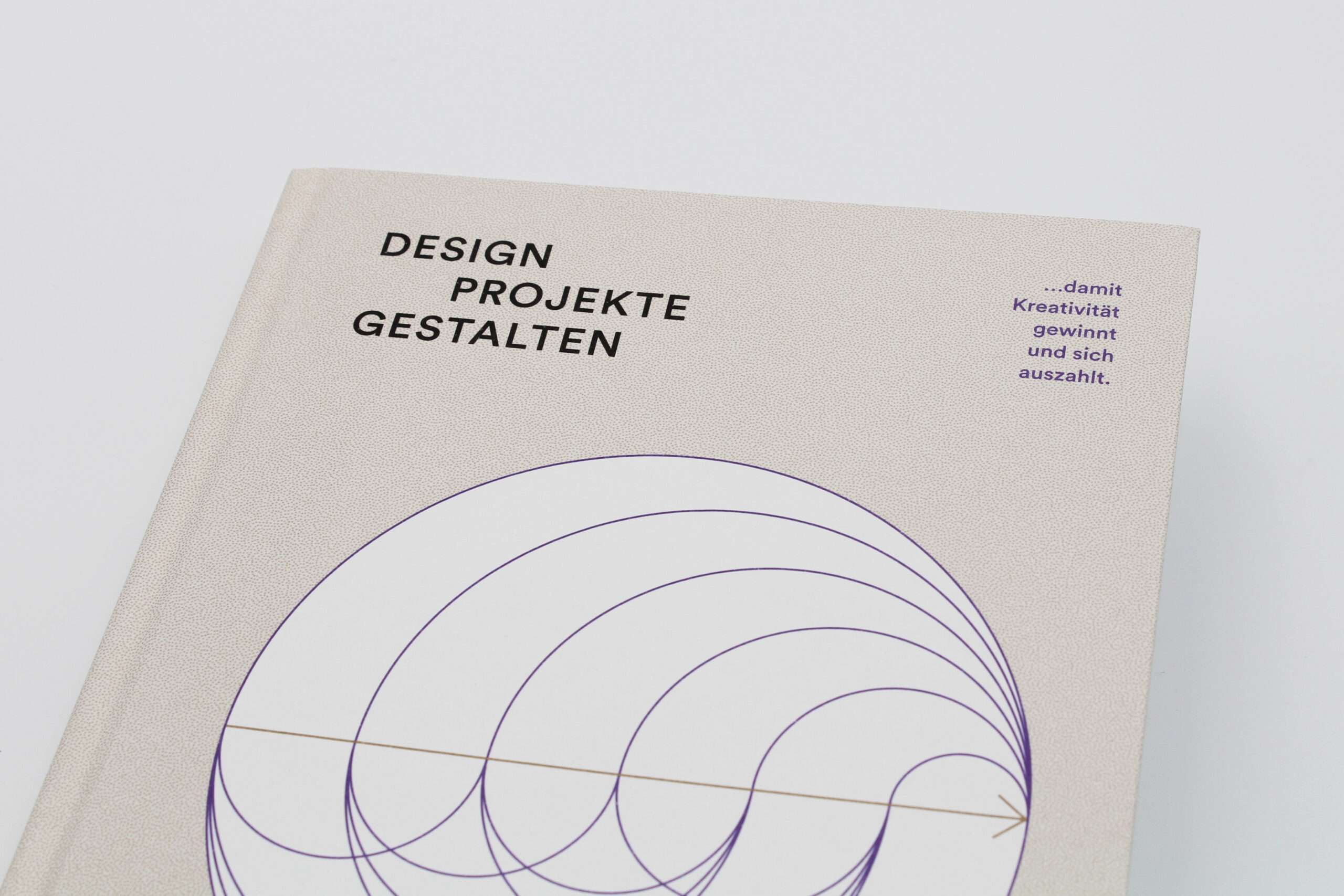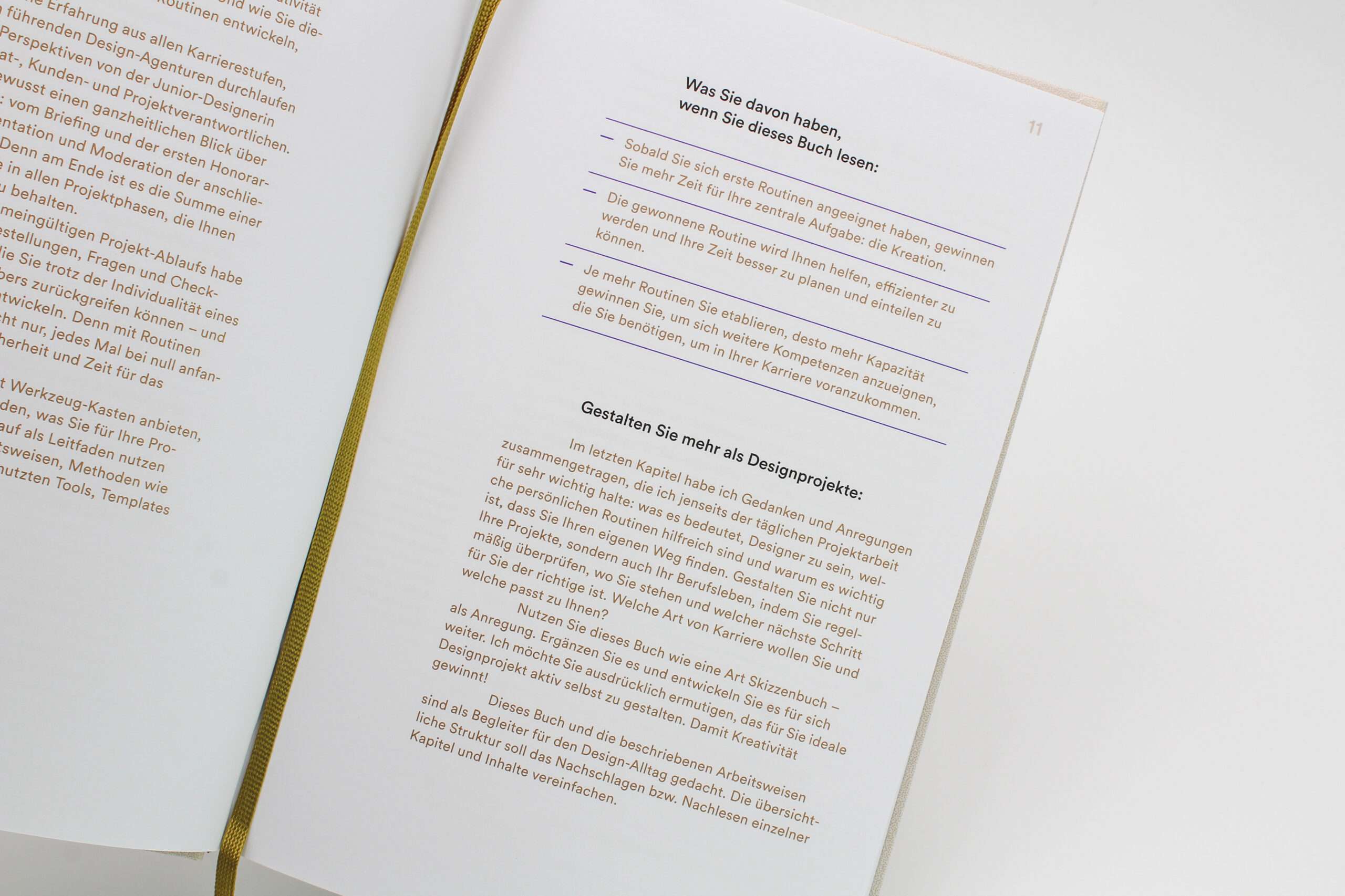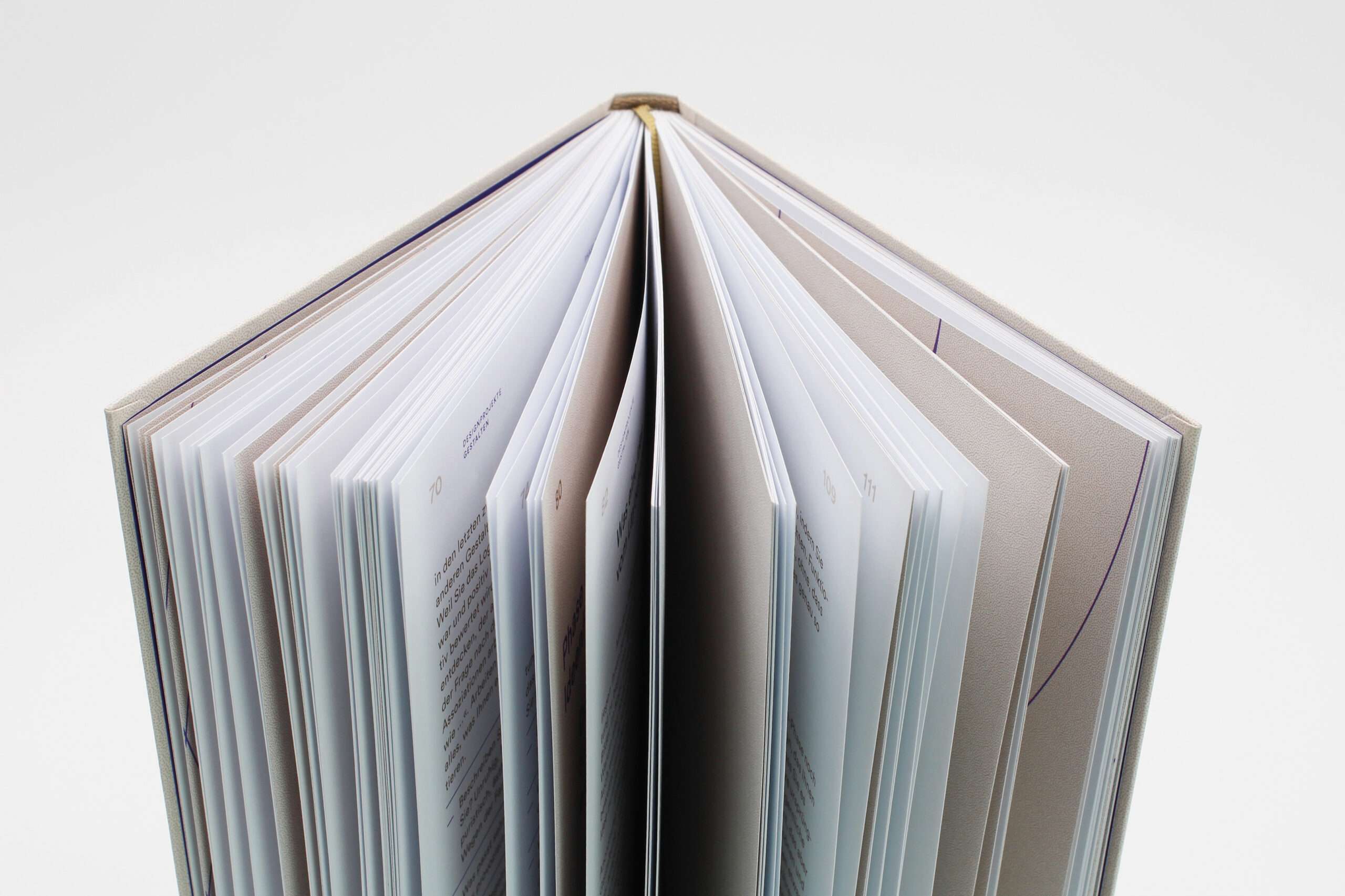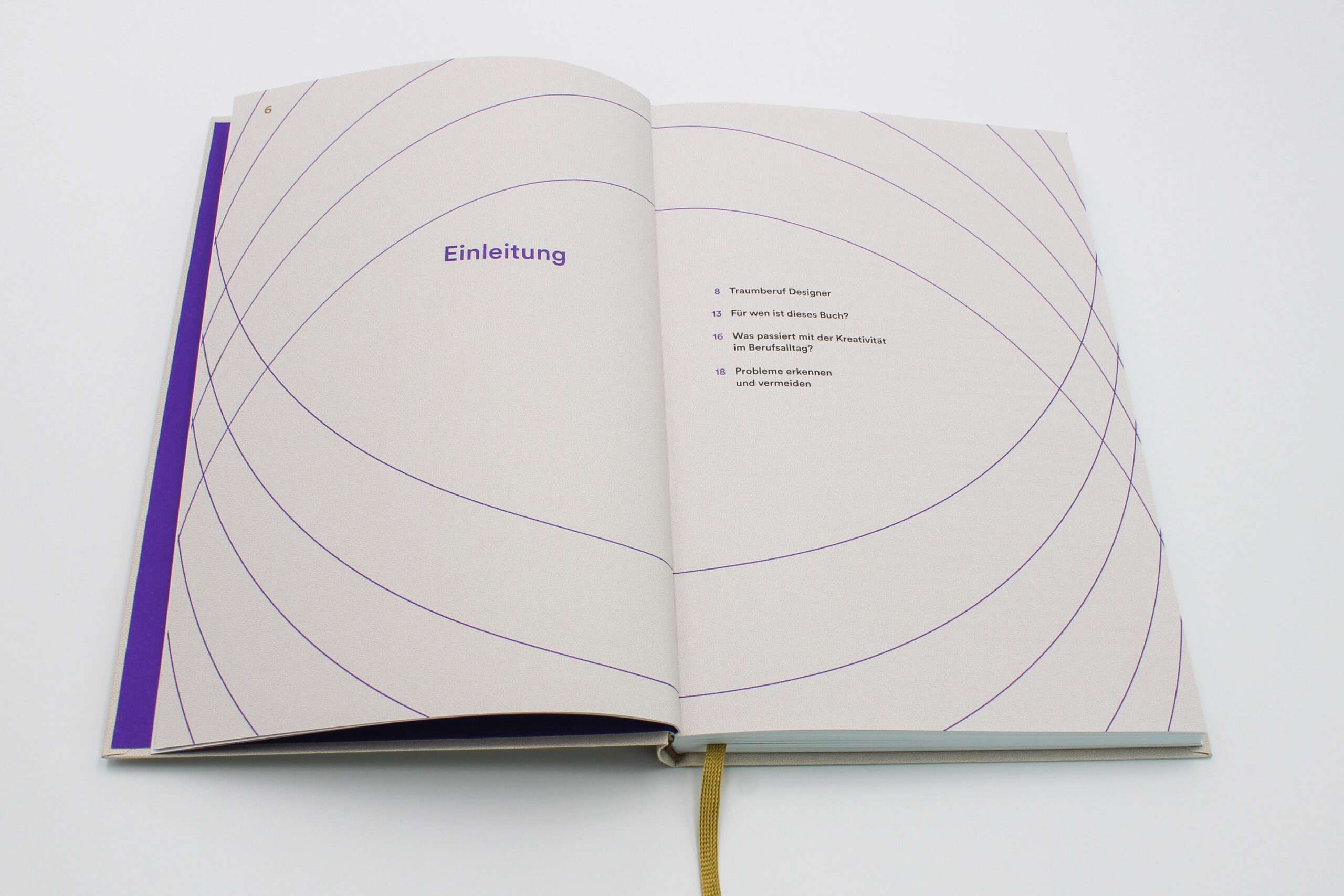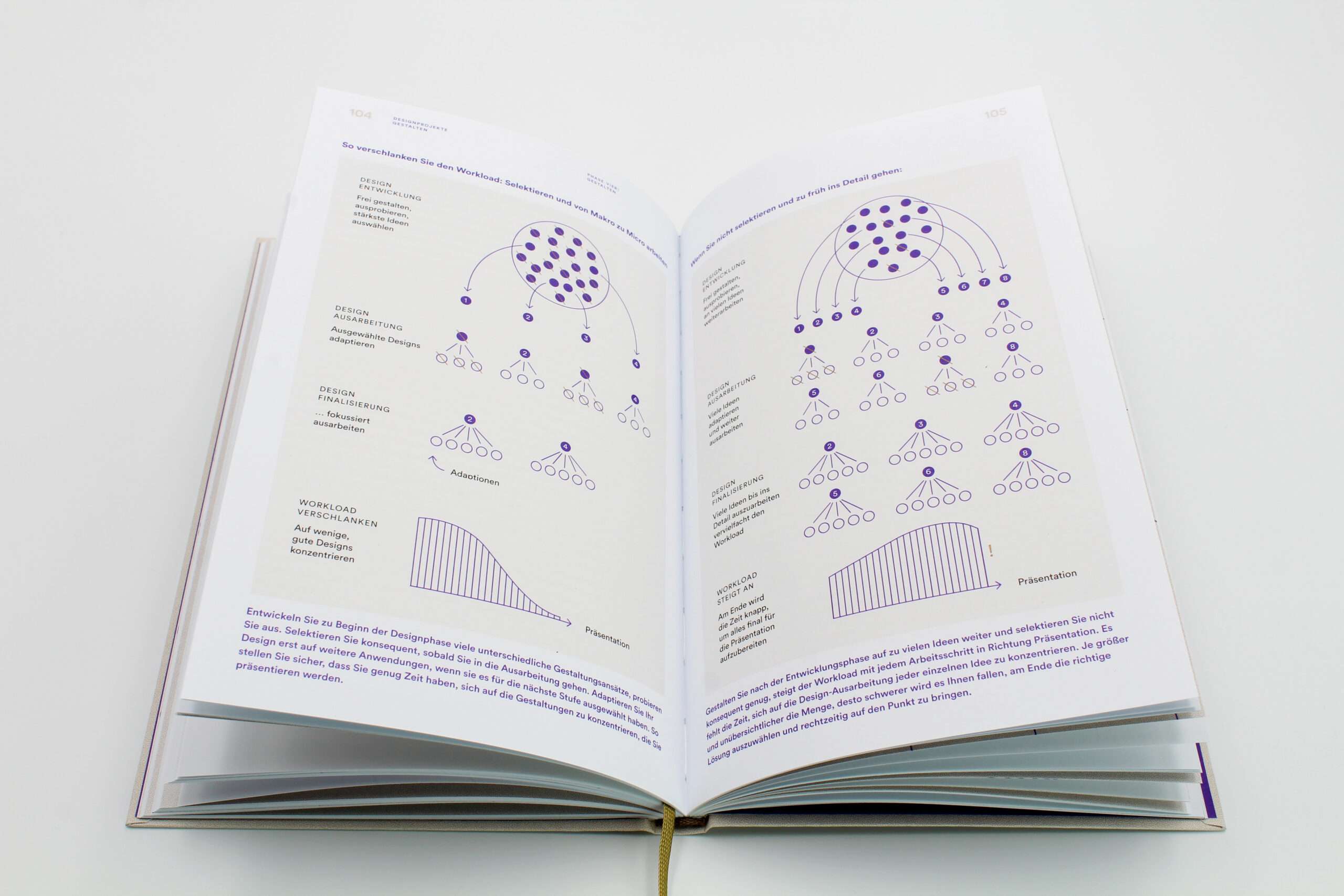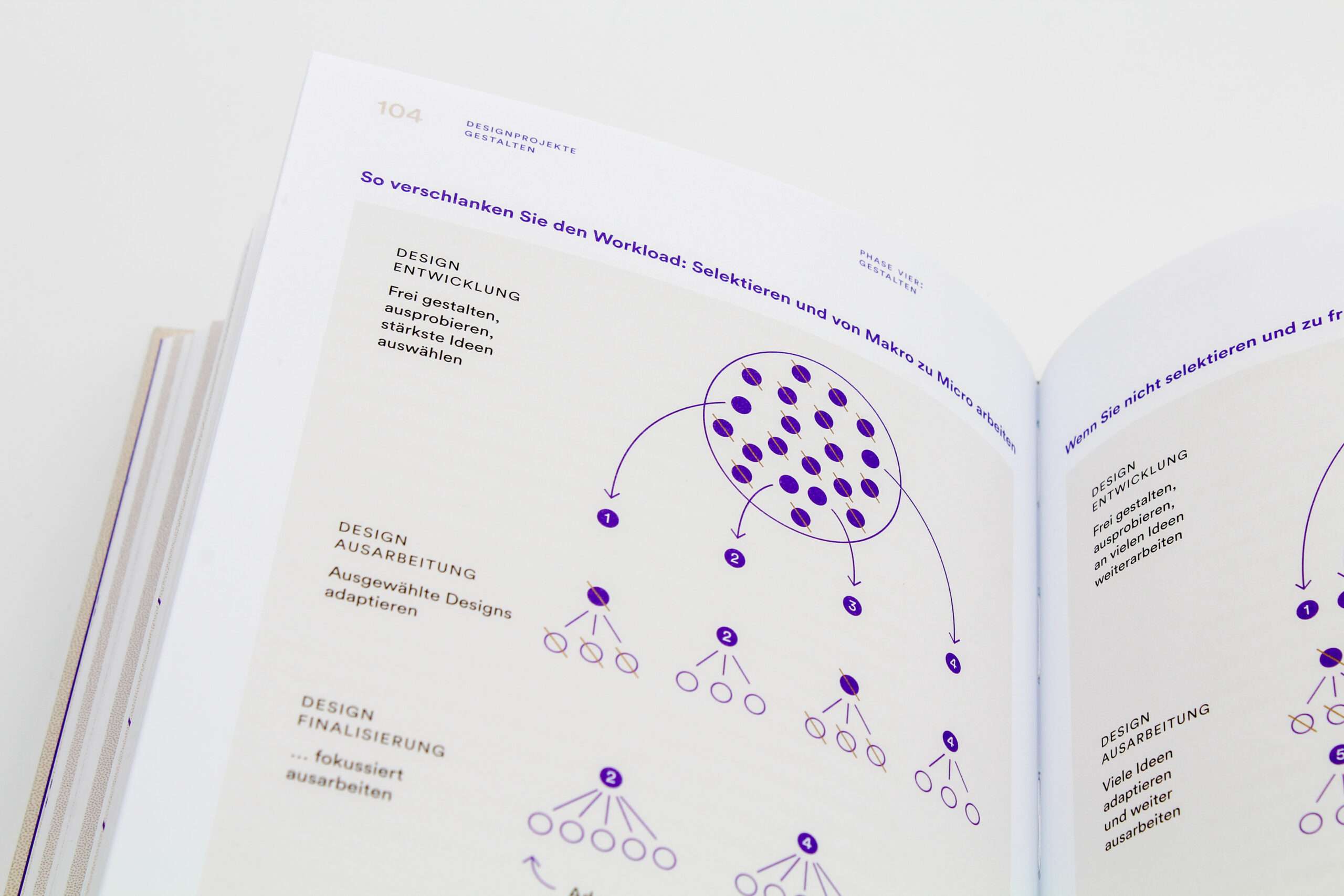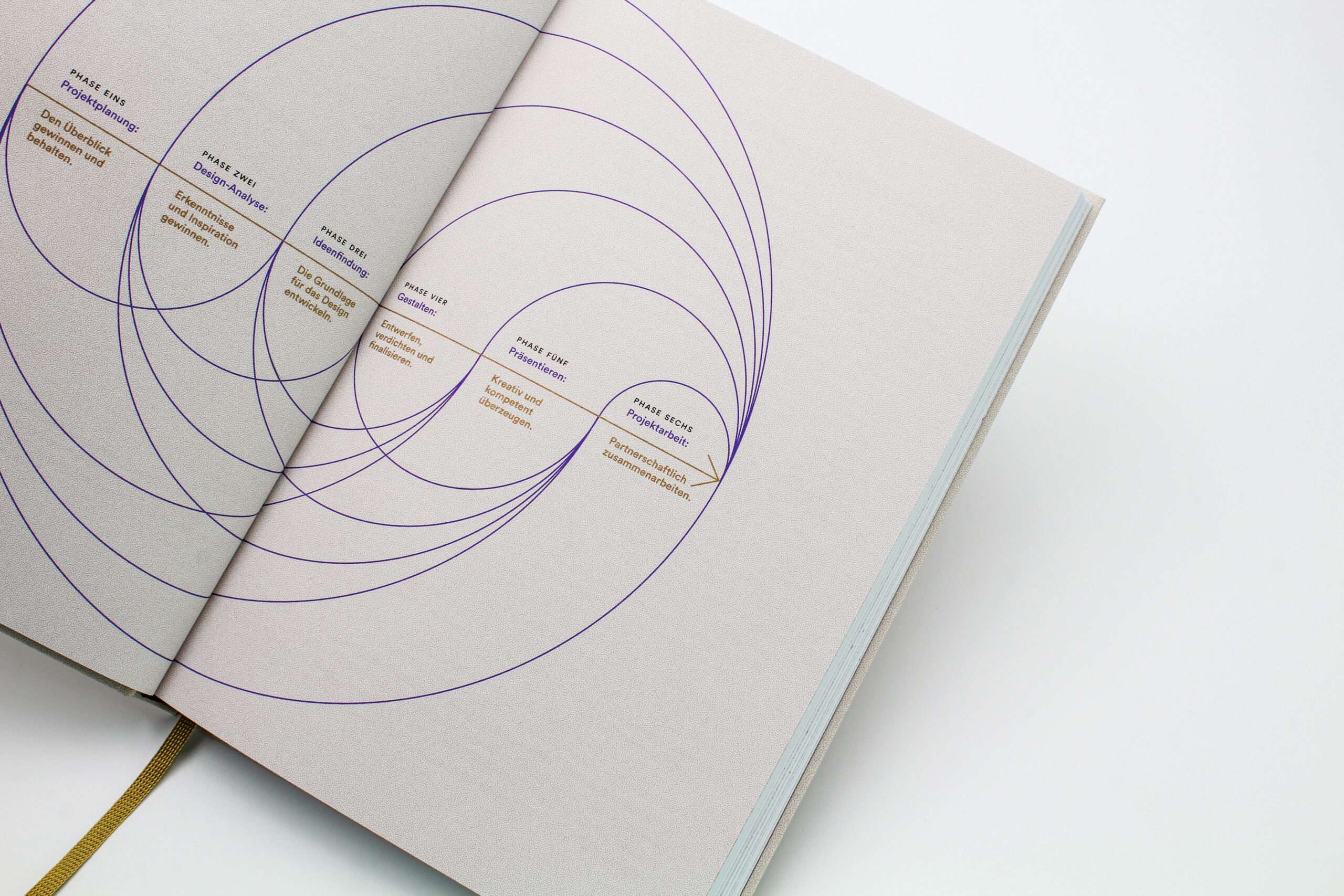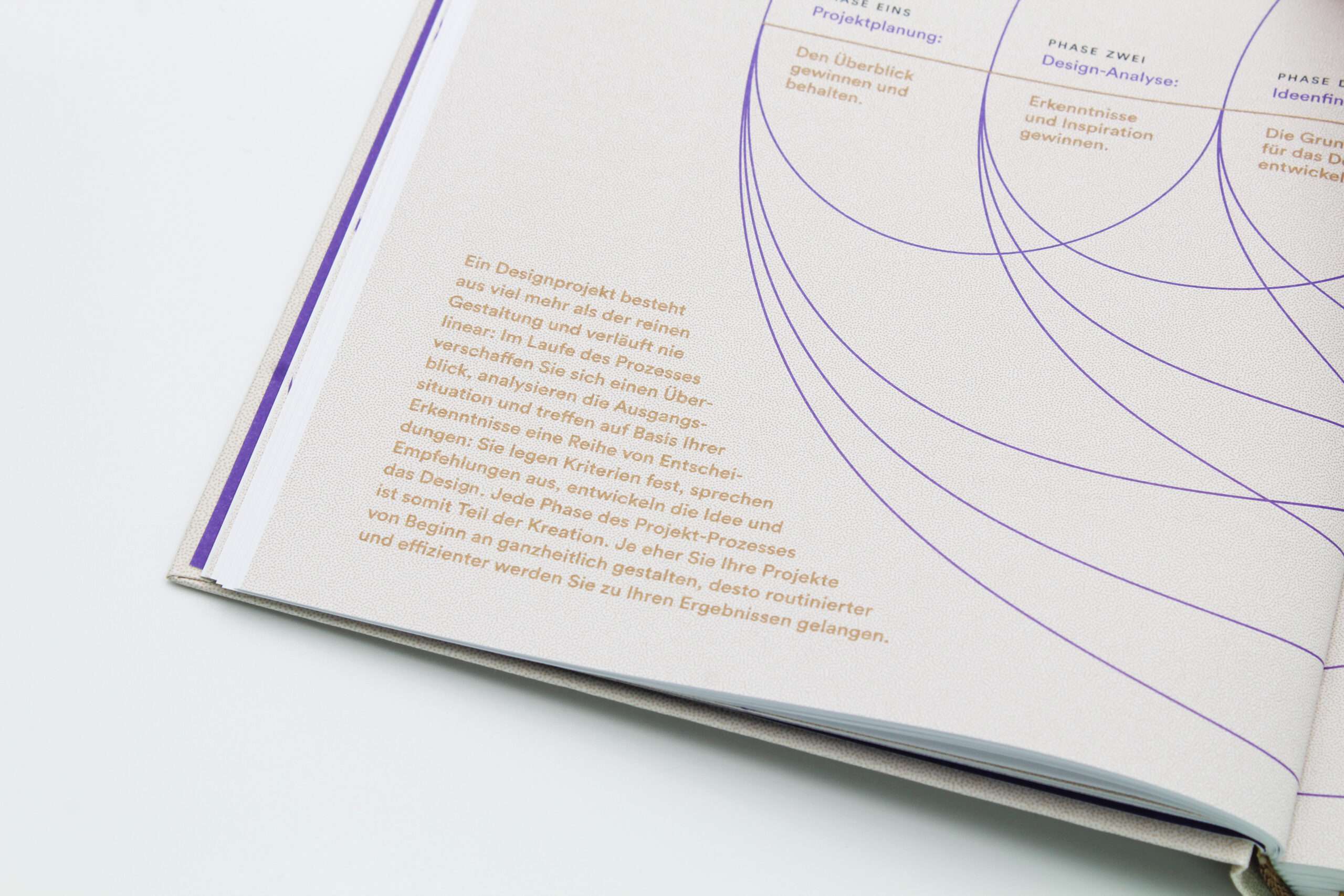
Damit Kreativität gewinnt – und sich auszahlt
Ihr Schlüssel zur Vier-Tage-Woche im Design
Wenn Sie den Designprozess selbst als Gestaltungsaufgabe verstehen … Wenn Sie Designprojekte souverän und effizient steuern … Wenn Sie Pitch und Präsentation von Beginn an mitdenken … Dann bleibt mehr Zeit für das, was Ihnen Spaß macht: die Kreation und Ihr Leben neben der Arbeit!
Auch Ihre Kalkulationen werden besser aufgehen, Präsentationen überzeugender ausfallen – und Respekt, Anerkennung und Arbeiten auf Augenhöhe sind Ihnen sicher.
Katrin Niesen hat zwanzig Jahre in einer großen Agentur Kreative geführt, bevor sie sich mit einem kleinen Team selbständig machte. Das Team trat den Beweis an, dass sich gute Kreation, finanzielle Sicherheit und freie Zeit eben nicht ausschließen. In diesem Buch stellt sie Ihnen den praxiserprobten Designprozess vor, der auch Ihnen den Weg zu mehr Arbeitszufriedenheit und weniger Arbeitszeit ebnet.
Mehr Arbeitszufriedenheit und weniger Arbeitszeit – und Antworten auf Fragen wie:
• Wie fange ich an?
• Wie plane und kalkuliere ich ein Projekt?
• Wie gehe ich mit ständigen Kostendiskussionen um?
• Wie nähere ich mich einem Thema, mit dem ich erstmal nichts anfangen kann?
• Was, wenn mir einfach nichts einfällt und ich nicht liefern kann?
• Was, wenn mein Team nicht liefert?
• Wie führe ich eine Design-Analyse durch und komme zu klaren Empfehlungen?
• Wie gelingt eine gute Design-Strategie?
• Wie präsentiere ich Ideen überzeugend?
• Wie setze ich Ideen in gute Kreation um?
• Wie und nach welchen Kriterien treffe ich die richtigen Entscheidungen im Design?
• Wie überzeuge ich Auftraggeber von mutigen Lösungen?
• Was kann ich tun, wenn ich das Gefühl habe, festzustecken und die Deadline naht?
• Warum fangen Projekte oft so gut an und werden dann chaotisch und anstrengend – und was kann man dagegen tun?
• Warum wird die Zeit am Ende immer zu knapp und wie verhindere ich das?
• Wie agiere ich sinnvoll, wenn der Zeitplan von Anfang an zu eng ist?
• Welche Optionen bleiben, wenn ich keinen/kaum Einfluss auf die organisatorischen Rahmenbedingungen habe?
• Was tun, wenn vor lauter Organisation kaum Zeit zum Nachdenken und Gestalten bleibt?
• Wie gehe ich mit widersprüchlichem Feedback um? Wie mit Kritik?
• Wie motiviere ich mich?
• Bin ich als Kreative:r gut genug – und wer entscheidet das?
Zu Ausstattung und Gestaltung
Weil Kreative nichts so sehr hassen wie Regeln und Routinen möchte Katrin Niesen Ihnen in Designprojekte gestalten zur Rettung Ihrer Freizeit aber doch die eine oder andere gute Gewohnheit ans Herz legen. Deshalb durfte dieses Buch nicht schwarzweiß sein, nicht im DIN-Format daherkommen, nicht nach Tabellen, Checklisten und Formularen aussehen und sollte doch genau die bereitstellen, um Ihnen Zeit für das Wesentliche zu verschaffen: die Kreation. (Das, warum Sie Designer:in geworden sind.) Und gerne zusätzlich Zeit für Ihre kreativen Leidenschaften neben der Arbeit, z. B. das Siebdrucken, Zeichnen  oder Draußen gehen …
Keine einfache Gestaltungsaufgabe für Eva Finkbeiner.
Sie wählt mutige Farben und eine Schrift, die auch in Bronze gedruckt noch super lesbar ist: Circular Std® (entworfen von Laurenz Brunner). Eva Finkbeiner hebt die besonders nützlichen Tipps und Tricks gestalterisch so hervor, dass Sie sie garantiert schnell wiederfinden. Und auch das spart Ihnen wertvolle Zeit.
Designprojekte gestalten
… damit Kreativität gewinnt – und sich auszahlt
Gestaltung Eva Finkbeiner
160 Seiten mit vielen nützlichen Checklisten, Diagrammen und zusätzlichen Arbeitsblättern zum Download
durchgehend dreifarbig gedruckt: Bronze, Schwarz und Violett
Format 15 x 23 cm
Flexcover mit rundem Rücken, Strukturpapierüberzug und einem bronzefarbenen Lesebändchen.
Inhaltsverzeichnis
Einleitung
Traumberuf Designer
Für wen ist dieses Buch?
Was passiert mit der Kreativität im Alltag
Probleme erkennen und vermeiden
Designprojekte gestalten
Phase eins
Projektplanung: Überblick gewinnen und behalten
Phase zwei
Design-Analyse: Erkenntnisse ableiten und Inspiration gewinnen
Phase drei
Ideenfindung: Die Grundlage für das Design entwickeln
Phase vier
Gestalten: entwerfen | verdichten | finalisieren
Phase fünf
Präsentieren: Kreativ und kompetent überzeugen
Phase sechs
Projektarbeit: Partnerschaftlich zusammenarbeiten
Routinen für Designer
Rourtinen für den Design-Alltag
Über den Umgang mit Kritik
Inspiration und persönliche Weiterentwicklung
Akquise-Routinen
Designer sein
Bin ich gut genug?
Anhang
Templateliste
Zum Weiterlesen
Über die Autorin